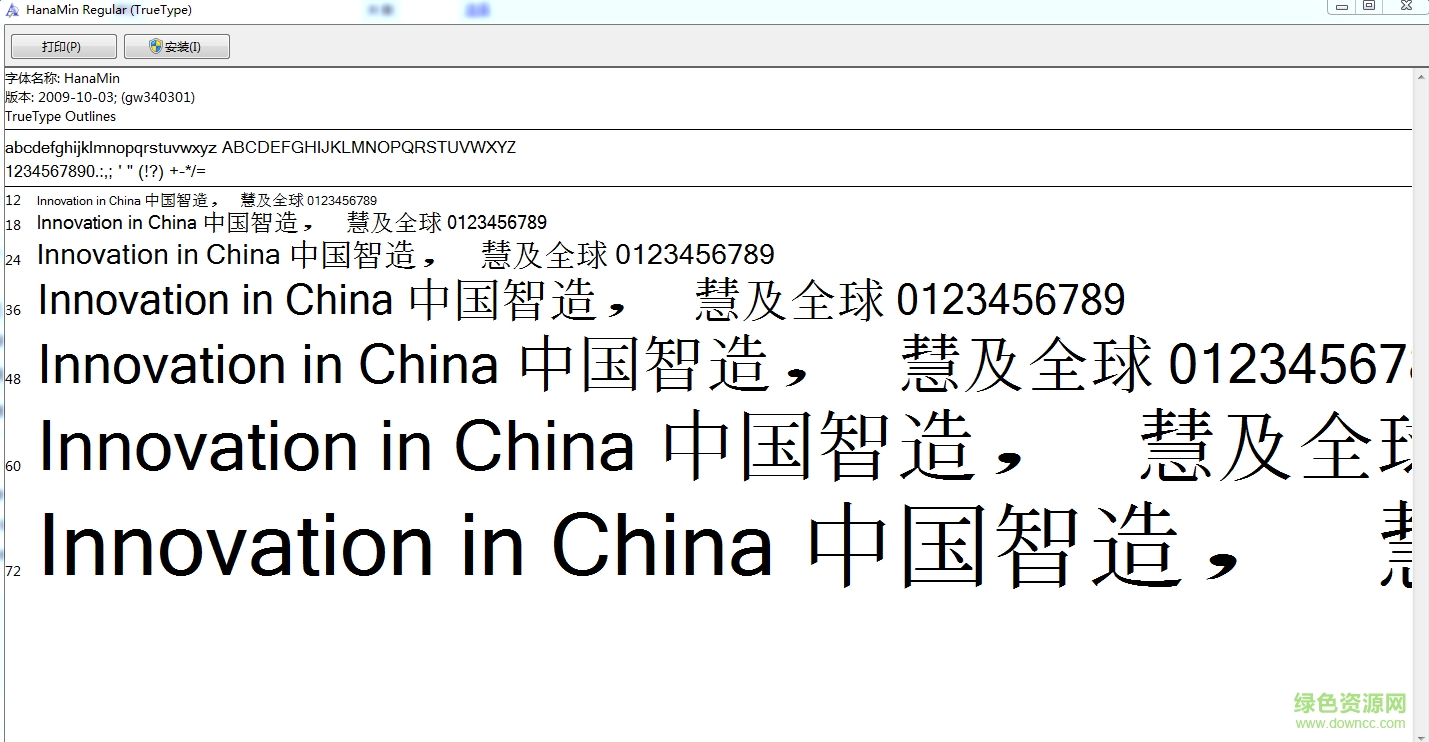
日本花園明朝體是一款ttf格式的日本hanamin字體,該字體與宋體比較相像,字形非常工整,適用于美工設(shè)計、平面設(shè)計等各個領(lǐng)域,喜歡的朋友快來綠色資源吧!
廣義的明朝體指的是日本、韓國等對宋體字的叫法。狹義則僅指一種日文電腦字體。
電腦漢字字體設(shè)計的最初,日本率先設(shè)計了明朝體,后來傳入韓國、中國臺灣,所以兩地也有明朝體的叫法。時至今日,由于中日兩國文字簡化方案的不同,兩國文字已經(jīng)有了很大的不同,明朝體也就徹底成為一種外文字體了